Типографика это: Что такое типографика и какие шрифты использовать на сайте
Разбираемся в основах типографики за 10 минут
Два главных типа чтения — линейное и информационное.
Линейное чтение — это книги и лонгриды с одной колонкой, где главное — не отвлекаться и погружаться в текст.
Информационное чтение — когда читаем не всё от начала до конца, а выборочно сканируем статью в поисках нужных ключевых слов и решаем, какую часть текста прочитать. Это другой ритм и другое восприятие.
Пример статьи для быстрого информационного чтения. Главные мысли выделены жёлтымТрекинг — расстояния в строке между символами.
Кернинг — регулирование межбуквенного расстояния для каждой отдельной буквенной пары. Например, в сочетаниях букв AW или Го расстояние между буквами может быть нулевым или даже минусовым, потому что одна буква идеально сочетается с другой, как две части пазла.
Без кернинга в некоторых комбинациях букв будут огромные непропорциональные апроши — межбуквенные пробелы.
Антиква — классический старый шрифт с засечками. Главная особенность — цепляет взгляд и замедляет чтение, благодаря чему читатель лучше усваивает информацию.
Гротеск — более современный шрифт без засечек. Читается легче и быстрее антиквы.
Брусковый шрифт отличается от обычной антиквы ровными прямоугольными засечками.
Рукописный шрифт выглядит так, будто его нарисовали кистью. Отличается плавными линиями с разной толщиной.
Прямое начертание — это классический машинописный шрифт.
Курсив — это лёгкий наклон букв вправо, как при рукописном письме.
Читается и воспринимается хуже прямого начертания. Подходит для выделения небольших частей текста: подписей, врезок, цитат.
Графема — это общий скелет буквы. Букву можно нарисовать или сложить из чего угодно, но благодаря единой графеме вы сможете отличить А от Б.
Разные варианты написания буквы А, соблюдающие общую графемуНасыщенность определяется толщиной линий. Чем толще линии, тем выше насыщенность.
Контраст определяется разницей толщины штрихов. Чем больше разница между тонкими и толстыми линиями, тем выше контрастность.
Пример шрифта с высокой и низкой контрастностьюШрифты с высокой контрастностью используют в модных журналах. Можно вообще отказаться от иллюстрации и собрать шрифтовые композиции, которые в соответствующем стиле будут смотреться круто и интересно, но у таких композиций низкая читаемость, поэтому использовать их лучше только в качестве акцидентных.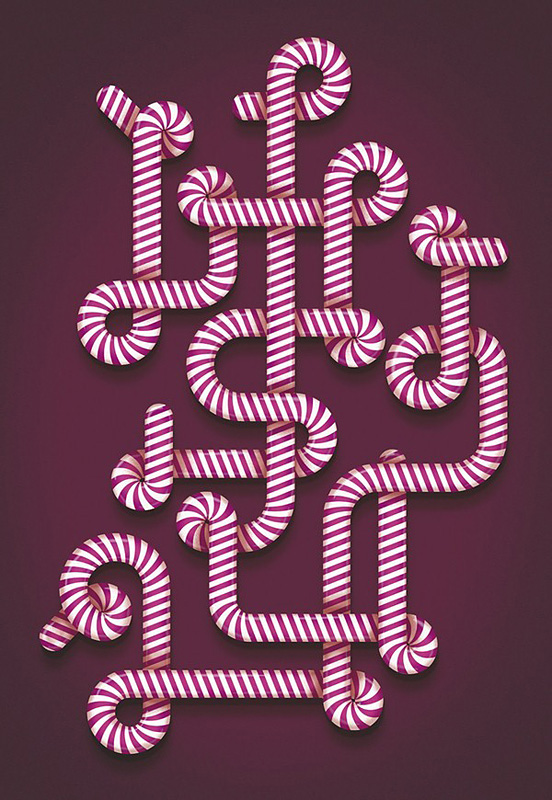
Акцидентный шрифт используют в заголовках, афишах, обложках книг, визитках и так далее. Его цель — привлечь внимание своей нестандартностью. Но чем необычнее выглядит текст, тем сложнее его читать, поэтому после акцидентного заголовка обычно идёт текст классическим наборным шрифтом.
Наборный шрифт используют в книгах, лонгридах, статьях и любых больших массивах текста. Его главная задача — сделать так, чтобы читать было легко и приятно, а глаза не уставали. Чем выше читабельность, тем лучше.
Примеры наборного и акцидентного шрифтаПропорциональный и моноширинный шрифты отличаются размерами литер.
Наглядный пример отличий пропорционального шрифта от моноширинногоВ моноширинном все буквы занимают одинаковую площадь, равную самой большой литере. Даже если английская буква i почти не занимает места, слева и справа от неё в моноширинном наборе будет много пустого пространства. Обычно его используют в таблицах, так как он помогает сохранить легкосчитываемую визуальную разрядность значений.
В пропорциональном занимаемая литерой площадь зависит от её размеров: английская i будет занимать в 2-3 раза меньше места, чем n. Такой набор экономит свободное место, поэтому в печатных изданиях используют только его. Если напечатать книгу моноширинным шрифтом, её объём и расход листов увеличится на 5-15%.
Типографика: искусство текста
4 — 2003Маргарита Григорян
Основа основ
Типографика на практике
Цвет
Если вы думаете, что книжки без картинок всегда очень скучные, то вы наверняка не знакомы с типографикой. Типографика это и наука, и искусство. Она превращает то, что принято называть голым текстом, в яркие и оригинальные графические образы.
По сути дела, типографика – это творческое преображение печатного текста в элемент графического оформления. Она обходится без использования иллюстраций и изобразительной графики, но с помощью моделирования и монтажа текста создает художественные образы. Именно поэтому типографика является неотъемлемой частью дизайна и оформительского искусства.
Главная задача типографики – доступно, ясно и в интересной форме донести до зрителя или читателя информацию. Как именно это сделать, остается на выбор специалистов по типографике – типографов. Они собирают в одно целое текст, шрифт, располагают шрифтовые элементы относительно друг друга и заданного пространства. Это может показаться простой и чисто технической задачей, однако на самом деле методами типографики можно создавать настоящие произведения искусства.
Типографика требует тонкого понимания процесса трансформации печатного текста в четкий визуальный образ, соответствующий значению заданной информации. Для этого существует множество различных приемов, например акцентирование смысловой нагрузки слова «оранжевый» при помощи написания его оранжевым цветом или же написание слова «маленький» небольшим кеглем. Также типограф может манипулировать гарнитурами шрифтов, разрядкой литер, их положением на макете, соотношением масштабов текстов и т.д. Поэтому типографов можно назвать художниками и поэтами одновременно.
Основа основ
Шрифт – это база для создания любой типографической композиции и, естественно, параметры шрифта ограничивают возможности типографа.
Чаще всего в типографике используются так называемые акцидентные и титульные шрифты, которые нецелесообразно применять для текстового набора. Они редко используются в мелком кегле, но хорошо смотрятся, как оформительские элементы при кегле покрупнее. Сегодня многообразие шрифтов постоянно пополняется новыми видами. Но, как ни странно, по мнению некоторых специалистов по типографике, обилие шрифтов является не показателем успеха, а наоборот, свидетельствует о недостаточной координации деятельности шрифтографов.
Типографика на практике
Огромное количество объявлений, вывесок и указателей выполнено в технике типографики. Широкое применение она находит и в малоформатных печатных изданиях; брошюры, флайеры, буклеты, проспекты и программки. Причина этого кроется в их предназначении привлечь внимание и донести информацию до читателя в условиях жестко ограниченного пространства бумажного листа. Типографика успешно справляется с обеими этими функциями, причем без перегрузки страниц тяжелыми иллюстративными элементами.
Не обходится без типографики и широкоформатная реклама. Поскольку взгляд задерживается на рекламном щите, как правило, не дольше чем на несколько секунд, информация на нем должна быть представлена в максимально сжатом виде. Такая реклама воспринимается сначала визуально, а лишь потом, если удастся привлечь внимание человека, происходит осмысление ее текстового содержания. При этом использование большого количества иллюстрирующих деталей может привести к негативному результату объявление оказывается перегруженным информацией и взгляд не успевает охватить одновременно и текст, и изображение и уж тем более правильно интерпретировать их. Здесь-то и приходит на помощь типографика, которая превращает текст в привлекающую внимание и легкую для восприятия графику. Проектируя широкоформатные рекламные плакаты, дизайнеры-типографы часто экспериментируют с соотношением масштабов текста и формата листа, находя порой довольно оригинальные композиционные решения. Именно в сфере рекламы у типографа появляется больше возможностей для трансляции заданного рекламодателем смыслового послания в композиционный образ.
Само собой, одной только широкоформатной рекламой применение типографики в рекламе не ограничивается типографическое оформление с успехом применяется и в печатной рекламе. Основные задачи здесь остаются теми же – привлечь внимание, заставить сначала всмотреться в образ, а затем и вчитаться в текст. Хороший пример – реклама «Finances, Trust, Consulting», разработанная дизайн-студией Open Design. Она представляет собой изображение прозрачной призмы, на гранях которой сделаны надписи «Деньги – это наука» и «Деньги – это искусство». Художники из Open Design использовали оригинальное и остроумное типографическое решение, заменив некоторые из букв кириллицы в надписи «Деньги – это наука» на греческие, которые, как мы знаем со школьной скамьи, широко применяются в науке, а в строке «Деньги – это искусство» – на музыкальные символы. Таким образом, смысловая нагрузка рекламы гармонично сочетается с ее визуальным исполнением. Нестандартное же решение делает рекламу заметной.
Широко используется типографика и в дизайне упаковки, причем наиболее часто она находит применение в парфюмерно-косметической индустрии. Практически все упаковки духов, как и этикетки на флаконах, выполнены с использованием типографики. Классическим примером может служить оформление легендарных духов «Chanel № 5», дизайн коробки которых не менялся с самого момента их создания в 20-х годах прошлого века.
Не устояли перед типографикой и просторы Всемирной сети. Существует довольно много Web-страниц, оформление которых построено исключительно на использовании оригинальной формы и начертания текста. Если такая страница с точки зрения дизайна создана грамотно, то она будет легко восприниматься зрителем и хорошо запоминаться. Поскольку в Web-дизайн типографика вносит элемент некоторой неформальности (все-таки в Интернете преобладает использование графических элементов для композиции и навигации), подобное оформление редко используется при создании корпоративных страниц, а вот среди сайтов дизайн-студий их становится все больше и больше. Один из наиболее известных и интересных сайтов такого рода – The Designers Republic (http://www.thedesignersrepublic.com/). Он представляет собой обширный каталог дизайнерских решений, и именно благодаря типографическому оформлению навигация среди огромного количества информации заметно упрощается. На главной странице The Designers Republic можно увидеть большую типограмму с надписью «Angryman» – текст, посредством монтажа превращенный в изображение «сердитого человека». Всмотревшись в эту типограмму, зритель увидит детали латинских литер, собранных в одно целое.
Часто в типограммах (или в «каллиграммах») на первый взгляд невозможно определить первоначальный облик отдельных символов, но, если присмотреться, можно различить их. При создании типограмм типографы обычно пользуются такими приемами, как искажение составных литер, изменение кегля и рисунка символов, а также намеренная деформация строк наборного текста. Самый простой и распространенный способ создания типограмм – верстка текста в форме описываемого в нем объекта (например, указатель, в котором размеры составляющих его букв подобраны таким образом, чтобы слово по форме напоминало стрелку). Но есть и более сложные разновидности типограмм, в которых текст становится нечитаемым, преобразуясь в картинку. «Angryman» с The Designers Republic – отличный тому пример.
Без типографики не существовало бы логотипов. Даже самые простые из них представляют собой типографические композиции, а многие и вовсе являются сложными типограммами. Бывает даже так, что шрифт, использованный в логотипе, сам по себе начинает восприниматься как неотъемлемая часть корпоративного имиджа компании, например, как известный шрифт Microsoft Sans Serif.
Типографика пользуется огромной популярностью и у авторов художественных постеров и плакатов, которые давно уже выделились в самостоятельный жанр изобразительного искусства. Они, как и рекламные публикации, вынуждены апеллировать в первую очередь к визуальному восприятию. Однако жанр постеров и плакатов не органичен такими жесткими рамками, как, скажем, печатная реклама, и поэтому дает дизайнерам большую возможность художественного самовыражения; отсутствие заданных рекламодателем слоганов и формулировок превращают текст в полноправный инструмент графического оформления. Крупный формат плаката только усиливает его выразительность. Любопытный пример – антирасистский постер, созданный дизайн-студией Open Design. На нем изображены символы четырех мировых религий, каждый из которых собран из печатного текста, взятого из священной книги другой веры. Например, мусульманский полумесяц набран текстом из Торы, а шестиконечная звезда Давида – строками из Корана. Однако значение подобных постеров может остаться непонятным без сопроводительной пояснительной надписи. В данном случае это строки «Они – это мы» и «Мы – это они», расположенные на красной ленте, согнутой буквой V символично, просто и понятно.
Типографика в веб-дизайне — правила и тренды современной типографики
“Веб-дизайн — это 95% типографики”, — сказал основатель компании Information Architect Оливер Райхенштейн. Так оно и есть: без качественной типографики ваш сайт будет неудобным для восприятия. В этой статье разберем основные виды типографики и современные тренды. Поехали!
Что такое типографика и зачем она нужна
Типографика в веб-дизайне — это свод правил оформления текста и графических элементов сайта, который несет определенный посыл, воздействует на эмоции и мотивирует посетителя к совершению целевых действий. В зависимости от направления сайта эти действия могут быть разными: подписаться на рассылку, читать больше статей, оставлять комментарии, совершать покупки. Таким образом, типографика идет рука об руку с продающим дизайном.
Есть еще дельное определение. Типографика — наука об эргономике текста, созданная для того, чтобы текст как можно легче читался и воспринимался посетителем сайта. Для этого должен соблюдаться баланс текстовых и графических элементов
Основные правила типографики
- Чем проще — тем лучше. Даже если появилось множество новых интересных шрифтов, эмодзи, анимаций — не нужно использовать все их сразу. Сайт будет аляпистым и совершенно не стильным.
- Сайт должен быть читабельным. Если выбирать между оригинальностью идеи и удобством для посетителя — любой веб-дизайнер не раздумывая выберет второе.
- Главное должно отличаться от второстепенного. Хорошая типографика сразу показывает, что тут самое важное, а что нет. Если элементы сайта спорят между собой и взгляд посетителя мечется, не зная, что выбрать — значит, типографика хромает.
- Правило золотого сечения. Мы уже писали о нем в статье про основные правила веб-дизайна. Если кратко — это деление элементов страницы сайта на пропорции в соотношении 3/2, или 5/3, и так далее. Чаще всего по этому принципу определяется соотношение рекламных блоков и текста.
- Текст важнее. Графика должна не перетягивать одеяло на себя и отвлекать от контента, а дополнять его и привлекать к нему внимание. Текстовая информация чаще важнее, чем картинки — а значит, графика должна быть на службе у контента, а не наоборот.
- Помните о гармонии. Не только в музыке она есть, как пелось в одной известной песне. На сайте все должно быть выполнено приятно глазу, гармонично и естественно. Хотите проверить? Просто дайте оценить сайт любому знакомому: пусть посмотрит свежим взглядом и выскажет честное мнение.
Основные понятия типографики и как их применять
О шрифт, ты — мир!
История шрифтов в типографике заставляет задуматься. На заре веб-дизайна считалось крутым использовать необычные шрифты по принципу “чем чуднее — тем моднее”. Со временем появилась тенденция к упрощению: сейчас предпочтение отдается простым крупным шрифтам. И обязательно читаемым.
Приведем несколько основных правил использования шрифтов на сайте:
1. Не используйте слишком много шрифтов. Мы все понимаем — хочется сделать свой сайт поярче и поинтереснее, но пожалуйста, остановитесь на двух-трех. Слишком большое количество шрифтов выглядит непрофессионально и нечитабельно. Подумайте о посетителе — легко ему будет подстраиваться под хотелки дизайнера? Да и сочетать много шрифтов будет непросто — как правило, в итоге таких экспериментов получается сборная солянка.
Например, хорошо сочетаются шрифты Georgia и Verdana — они визуально похожи и гармонично дополняют друг друга. Шрифты Baskerville и Impact, напротив, имеют разную ширину символов, и второй просто “убивает” первый.
2. Используйте стандартные шрифты. Если ваш веб-дизайнер — не суперпрофессионал, лучше не рисковать и выбрать знакомые всем true-шрифты, которые давно зарекомендовали себя. Это, например, системные Arial или Calibri, можно также использовать шрифты Google (это бесплатно) или Adobe Typekit (по подписке) или поюзать онлайн-конструкторы. Вариантов масса!
Внимание! Этот способ могут не применять те, кто хочет сразу громко заявить о себе или создать фирменный стиль сайта. Вот тут можно экспериментировать вволю — конечно, заручившись помощью хорошего дизайнера. С осторожностью обращайтесь с готическим, старославянским шрифтами, Comic Sans — они, как нам кажется, давно себя изжили и не всегда уместны. Хотя на многих ресурсах до сих пор популярны.
3. Буквы должны читаться! Есть некоторые шрифты, в которых отдельные буквы можно перепутать. Например, I и L в английской раскладке, “н” и “м”, “т” и “ш” — в русской. Особенно сложно бывает читателю, когда еще и расстояния между буквами маленькие. Остерегайтесь таких шрифтов!
4. Выбирайте адаптивный шрифт. Про адаптивный дизайн сайта, который одинаково хорошо просматривается и грузится на разных устройствах, уже всем известно. Пользователи заходят в сеть со смартфонов, планшетов, ноутбуков, лэптопов — размеры экрана у них у всех разные, разрешение тоже отличается. Шрифт — часть адаптивного дизайна, он должен так же хорошо читаться с различных устройств и в разных размерах. Избегайте слишком маленьких шрифтов, чтобы пользователю не приходилось приближать текст и совершать дополнительные действия.
Искусство цвета
1. Играйте на контрасте. Цвет текста и фона для него должны различаться. Серый на сереньком — так себе тренд. Чем больше бросается в глаза контраст — тем гарантированнее он привлечет внимание пользователей. Чем меньше шрифт, тем более он должен быть контрастным, и наоборот.
Какие цвета можно сочетать? Используйте базовые принципы сочетания цветов. В этой схеме нет черного и белого — они априори сочетаются с любым цветом. Наиболее контрастным, кстати, считается сочетание черного и желтого. Взять наш “Тинькоф-журнал” — они использовали это правило на все сто.
2. Смелее, детка! В моде техники градиента, дуплекс — использование двух цветов и их полутонов, трехмерные объемные изображения, картинки, нарисованные вручную и другие тренды веб-дизайна 2018 — ограничений практически нет. Все зависит от вкуса и чувства стиля вашего дизайнера.
3. Выделяйте цветом важнейшие текстовые блоки и рекламу — чтобы посетитель сразу обратил на них внимание. Многие дизайнеры советуют избегать красного и зеленого цветов — заботятся о больных дальтонизмом. Между прочим, среди мужчин дальтоников аж восемь процентов — серьезное число.
Оформление текста
“Крылья, ноги, главное — хвост!” — если перефразировать фразу из культового мультика, то же самое можно сказать и о тексте. Цвет и шрифты, конечно, важны, но оформление текста все же играет главную роль в восприятии сайта посетителем. Рассмотрим современные тенденции оформления текста:
1. Используйте пиктограммы, значки, эмодзи. В типографике как в жизни: если люди активно используют смайлики для общения, значит, нужно применять их и на сайтах. Мир веб-типографики уже никогда не станет прежним: пиктограммы, смайлы и значки стали важной частью текста. Это делает его более динамичным и близким к пользователю.
2. Форматируйте. Это незыблемое правило: если не хотите, чтобы ваш интересный и полезный текст превратился в одну большую простыню — ставьте заголовки и подзаголовки, не забывайте про маркированные списки. Обязательно выделяйте абзацы — сплошной текст читать просто невозможно. Считается, что оптимальная длина абзаца составляет 3-5 строк.
Для того чтобы расставить акценты, выразить главные мысли — прибегайте к выделению жирным, подчеркиванию и курсивом. Эффект зачеркивания круто смотрится, когда надо добавить иронии. Из журнальной типографики к нам пришли вынос мыслей в цитаты, красивое оформление первых букв нового абзаца.
3. Забудьте про капслок! Тренд выделять главное капсом давно умер: сейчас большие буквы воспринимаются как крик и вызывают у читателя лишь негатив. Большие буквы уместны лишь в заголовках, да и то не всегда. Привлекать внимание с помощью капса уж точно не рекомендуется.
4. Ограничьте длину строки. Помните базовое правило типографики: текст важнее графики, особенности дизайна не могут диктовать условия верстке текста. Если дизайн вашего сайта предполагает длиннющую строку — проще поправить дизайн, чем заставить читателя дочитать ее до конца. Читабельность превыше всего!
Эксперты говорят, что оптимальное количество символов на строку — не более 60. Если меньше — читатель будет слишком быстро возвращаться в начало строки и сбивать ритм чтения. Если больше — сложно будет сосредоточиться на тексте: пока подойдешь к концу строки, забудешь о том, что написано в ее начале.
Внимание! Это правило актуально для текстов, которые читаются с ПК. Если речь идет о мобильном устройстве, длина строки должна составлять не более 30-40 символов — больше в экран просто не влезет. Ну вы поняли: адаптивный дизайн — наше все.
5. Следите за межстрочным интервалом. Чем он больше — тем больше воздуха в тексте, тем проще читателю пробираться через слова и символы. Обычно размер интервала должен быть на 30% больше высоты символов. Посмотрите, какая колоссальная разница между первым и вторым примером!
Тренды типографики последних лет
Типографика переживает сейчас настоящий расцвет: мы наблюдаем буйство стилей и эффектов, разнообразие визуальных составляющих, новые способы воздействия на посетителей.
Крупная типографика
Пожалуй, самый главный тренд последних лет — крупная типографика. Давайте разберем, зачем она нужна:
- привлекает и удерживает внимание посетителя. Сложно не заметить крупные шрифты, яркие цвета и особое расположение самого важного текста на странице. На сайте интернет-магазина, например, таким текстом будет призыв к действию, информация о скидках и поступлении новых коллекций. На новостном сайте — самая актуальная в данный момент статья. Большой текст — как неоновая надпись в небе: ну посмотри же на меня, прочитай меня, выбери меня, купи меня;
- вызывает эмоции. Если написать одну и ту же фразу мелким и крупным шрифтом — посетитель стопроцентно отдаст предпочтение второму варианту. Вопрос еще и в том, как написать — если удастся воздействовать на чувства посетителя — велик шанс, что он вернется и станет вашим постоянным посетителем. Если за громким слоганом стоит личность создателя сайта — эффект может быть ошеломительным. Главное — не только сказать, но и кем это сказано;
- позволяет определить главное. Все слышали про эффект баннерной слепоты — когда посетитель бегло сканирует взглядом текст, не задерживаясь на отдельных элементах. Крупный заголовок или рекламный баннер позволяет отделить зерна от плевел и остановить взгляд на самом главном. Заголовок помельче — информация второго уровня важности. Ну и так далее.
Большие шрифты
Жирный, еще жирнее! Это не оскорбление, а тенденция шрифтов последних лет. Чем больше и жирнее шрифт, да еще и с насечками — тем более современной будет ваша типографика. Кроме того, такие шрифты отлично читаются с мобильных устройств — мы же знаем, что все больше людей заходят на сайты со смартфонов и планшетов.
Сломанные сетки
Макеты с классической сеткой уже не в моде — дизайнеры отказываются от них и буквально пускаются во все тяжкие! Типографика сайта все больше напоминает издательский дизайн. Разметка на блоки, строгое количество колонок текста, модули уже не придерживаются строгих правил и живут своей жизнью. Каркас сайта может быть совершенно разным — главное, чтобы посетителям нравилось.
Больше движения!
Активно используйте гифки, анимацию, 3D-типографику — это оживляет сайт, привлекает внимание посетителей и выделяет ваш дизайн на фоне других. Особенно хорошо эти приемы работают при создании фирменного стиля сайта и персонализации личного бренда. За рубежом анимация давно популярна — у нас еще не все оценили ее возможности. Не упускайте шанс!
Понравилась статья? Обращайтесь в IDBI — мы знаем о типографике все и поможем разработать ваш сайт с учетом новых тенденций.
Леонид Рабинович «Что такое типографика?»
Данная статья написана Леонидом Рабиновичем и опубликована в его персональном блоге. Статья дает вводную информацию для начинающих изучать типографику, верстку и шрифт.
Текст — это последовательность слов. Текст остается текстом, вне зависимости от того, где он находится. Я могу написать «Люблю эспрессо и омлет» и распечатать это на бумаге, могу отослать сообщением ВКонтакте, могу просто сохранить текстовый файл и держать у себя на компе. Текст будет одинаковый, а носители разные.
Но когда мы печатаем (пишем, набираем и т.д.) «Люблю эспрессо и омлет» — в силу вступает типографика. Любой отображаемый текст — типографика. Без разницы на каком формате он написан.
Типографика влияет на содержание или смысл, то есть может решать разные задачи. Например, когда мы читаем книгу, нам важно чтобы наши глаза не перескакивали со строчки на строчку, чтобы шрифт был читаемый, чтобы мы легко ориентировались в содержании. Или когда на дороге нам встречаются разные знаки. В этом случае типографика должна быть ясна, а шрифт считываться за доли секунд. Представьте что будет, если весь текст на указателях писать каллиграфией.
Подумайте в чем разница между двумя следующими страницами: в тексте или типографике?
Текст ок
Текст не ок
Разница только в типографике. Этот пример ясно показывает как типографика влияет на комфорт и удобство, в данном случае, чтения.
Можно ли отнести типографику к искусству, я не знаю. Но думаю, что можно. По сути типографика должна быть функциональна, например функция передачи информации, и эстетична — подать информацию красиво.
Я считаю, что типографика — это основа всего графического дизайна. С помощью слов мы можем больше и точно передавать информацию, нежели чем с помощью картинок.
(!) Шрифты являются частью типографики, но типографика выходит за рамки шрифта.
Выводы:
- Типографика — это любой отображаемый текст.
- С помощью типографики можно решить разные задачи, влиять на удобство восприятия и на содержание предмета.
Шрифты — лишь часть типографики.
Почитать по этой теме:
http://artgorbunov.ru/bb/soviet/20140101 — совет Антона Шнайдера о значении типографики.
http://pajasu.livejournal.com/1241317.html — Принципы хорошей экранной типографики (кратко)
http://www.artlebedev.ru/kovodstvo/business-lynch/kagarov — Бизнес-линчи Эркена Кагарова (он всегда объясняет почему «типографика хуевая», например)
Следующий пост будет по теме:
Для кого нужна типографика?
Автор: Леонид Рабинович
Типографика в дизайне | Статья в журнале «Молодой ученый»
В статье описывается понятие типографики. Раскрывается определение шрифта и его составляющих. Подробно рассматриваются правила работы с типографикой в веб-дизайне. Автор уделяет внимание важности соответствия шрифта проекту.
Ключевые слова: типографика, шрифт, адаптивный дизайн, засечка, веб-дизайн.
Типографика одна из важных составляющих дизайна и ключевой инструмент при проектировании сайтов. Люди взаимодействуют с ней на протяжении многих веков. В данной статье большое внимание уделяется рассмотрению типографики в контексте веб-дизайна.
Современная типографика — это искусство, которое призвано сделать сложный материал простым, а неинтересный товар — популярным [3].
Неотъемлемая и главная часть типографики — шрифт.
Шрифтом обычно называют графическую систему изображения знаков, имеющую свойственное только ей начертание [2]. Единицей шрифта считается буква.
Русскоязычные специалисты и обычные пользователи в большинстве случаев используют кириллические и латинские шрифты. Кириллический шрифт моложе латинского. Это связано, в первую очередь, с пересмотром состава кириллицы Петром I. Была проведена реформа, и для светской и уставной печати начали использовать антикву. Последующие века шрифт трансформировался и видоизменялся. Это длительный процесс, который происходит и сейчас.
Шрифт отражает идею проекта, так как способен повлиять на отношение к проекту. Существует несколько категорий шрифтов. Во-первых, шрифты делятся на две большие группы: с засечками и без засечек. Это необходимо знать как типографам и дизайнерам, так и верстальщикам.
Засечка, или сериф, — один из важнейших элементов шрифта. Настолько важный, что, даже если в самом шрифте нет засечек, упоминание о них все равно есть в названии класса таких шрифтов: sanserif — «без засечек» [1].
Существют следующие виды шрифтов:
— — Антиква — шрифты с засечками.
Антиква подразделяется на следующие категории: старого стиля, переходная, нового стиля, латинского стиля, брусковая. Первая наборная антиква поялилась в Италии и Германии в начале XV века.
— Гротески (рубленные) — шрифты без засечек.
Классификация гротесков: старые гротески, новые гротески, геометрические, гуманистические, антиква и прочие.
— Готические — данные шрифты были распространены в XIII-XVI веках. Различают следующие виды готических шрифтов: текстура, швабахер, фрактура, ротунда.
— Акцидентные — предназначенные для акцидентного набора. К ним иногда относят и рукописные шрифты.
Следует подробнее остановиться на акцидентных шрифтах. Акцидентный шрифт отличается от наборного своей декоративностью, выразительностью и архитектурой. Он может быть менее читабелен, но главная информация должна считываться посредством визуальных образов. Основная цель акцидентного шрифта — привлечь внимание потребителя, пользователя или читателя.
Из этого следует, что у каждой из этих шрифтовых групп свои задачи. Гротески XX века хорошо справляются с нейтральными задачами. Шрифт передает потребителю не только прямое содержание сообщения, но и вызывает у человека определенные ассоциации. Этот эмоциональный отклик зачастую субъективен, ведь он основывается на жизненном опыте человека и степени его образованности, однако посредством опроса фокус-групп были выявлены схожие реакции на определенные виды гарнитур [2].
То есть, необходимо смотреть на все шрифты через контекст истории и принадлежности к стилю. Это необходимо для передачи характера бренда. Дизайнеру следует для начала выявить задачу и только потом подбирать шрифт. Многие люди не замечают соответствия шрифтов для айдентики или сайтов, в которых выбранная гарнитура используется. Но если потребитель не осознает этой взаимосвязи, совершенно не значит, что ее нет. Мы можем испытывать когнитивный диссонанс или недоверие к бренду на интуитивном и подсознательных уровнях.
Есть определенные правила работы с типографикой. И если в графическом дизайне и плакатном искусстве дизайнеры часто нарушают правила для достижения определенных декоративных эффектов, то не стоит ими пренебрегать в верстке книг и журналов, а также в веб-дизайне и разработке мобильных приложений.
В контексте веба правильная работа с типографикой играет важную роль. Одной из главных причин этого является важность структурирования контента в веб-пространстве. Это продиктовано феноменом клипового мышления.
Чем больше элементов использовано, например, на сайте, в буклете или листовке, тем разнообразнее они по своему содержанию и оформлению, тем выше потребность в четкой структурированности пространства. В данном случае основной задачей типографики является становление частью графических композиций [5]. Правила типографики обширны, ибо они включают в себя: все параметры шрифта (начертания, кернинг, кегль, интерлиньяж и т. д.), расположение текста, тонкости расстояний между параграфами, красной строки в русской типографике, её уместное использование, а также расстояние между заголовками и основой массой текста и т. д. [4].
Рассмотрим основные правила работы с типографикой в вебе.
— Размер пункта — это размер шрифта. В печати наиболее удобный диапазон для основного текста — 10–12 пунктов. В Интернете — 15–25 пикселей.
— Межстрочный интервал — это расстояние между строками по вертикали. Он должен составлять 120–145 % от кегля. При верстке сайта, пользуясь каскадными таблицами стилей (CSS), можно использовать свойство line-height.
— Длина строки — это ширина текстового блока по горизонтали. Длина строки должна составлять в среднем 45–90 символов в строке
— Для грамотного структурирования контента важно использование различных начертаний. (Regular, Bold, Light).
— Висячих предлогов следует избегать.
— Если расстояние между символами выглядит неровно, можно поправить его с помощью кернинга, руководствуясь правилом: «Пространство между символами должно быть одинаковым».
При соблюдении этих правил проект будет выглядеть композиционно правильным, текст будет хорошо считываться и восприниматься пользователем.
В заключение необходимо подчеркнуть, что типографика в дизайне является первостепенным элементом, наряду с композицией. Она важнее анимации и ярких графических решений. Кроме того, она выполняет функции инклюзивного дизайна, рассчитанного на доступность всем. Поэтому необходимо выбрать правильный и соответствующий идеям проекта шрифт, подобрать оптимальные размеры, кегль и интерлиньяж. В веб-дизайне функциональность всегда важнее графических решений. Дизайнеры делают продукт для человека, и он должен быть удобным, простым и понятным.
Литература:
- Гордон Юрий. Книга про буквы от Аа до Яя. — Москва: Издательство студии Артемия Лебедева, 2006. — 384 с.
- Каменская А. А. М. Е. Карагодина Основные принципы работы со шрифтами в графическом дизайне // Дизайн и архитектура: синтез теории и практики: сб. науч.тр. — Краснодар: Кубанский гос. ун-т, 2018. Вып. 2. — С.131–134.
- Любодарская К. В. Графический дизайн в системе маркетинговых коммуникаций на b-2-b рынке // Маркетинговые коммуникации. 2013. № 2. С.86–95.
- Мамаева Д. М. Взаимосвязь типографики и фирменного стиля. [Электронный ресурс]. — URL: https://www.elibrary.ru/item.asp?id=43131906
- Старикова Е. А. Типографика как новая современная форма коммуникации в дизайне // Лучшая научная статья 2016: сбрник статей II Международного научно-практического конкурса. — Пенза: МЦНС «Наука и просвещение». — 2016. — С.67–72.
Основные термины (генерируются автоматически): шрифт, засечка, CSS, XIII-XVI, акцидентный шрифт, век, длина строки, идея проекта, правило работы.
Типографика, история и задачи. Типографика, история и задачи С кем работают графические дизайнеры
Типографика – процесс и искусство разработки архитектуры коммуникации; моделирование, графическое оформление материала посредством набора и верстки, на основе определенных правил, специфических для данного языка.
Типографика — это искусство предоставления текстовой информации, преображение текста в графическое оформление, основа графического дизайна.
Термин типографика происходит от греческого τύπος — отпечаток + γράφω — пишу) — искусство оформления печатного текста.
Типографика – это, с одной стороны, набор правил, определяющих использование шрифтов и оформительских средств, с другой стороны – искусство графического дизайна.
Цель типографии – упростить коммуникацию с аудиторией, улучшить восприятие передаваемой информации.
Задачи типографики , наиболее творческого этапа оформления текста, предполагают:
- определение параметров для последующих процессов набора, вёрстки и допечатанной подготовки;
- способствование передаче эмоции, настроения, отношения задуманных автором, вовлечение в чтение и изучение;
- моделирование вида и формы контакта аудитории с объектом авторского и дизайнерского творчества;
- сделать текст наиболее оптимальным, ясным, максимально обеспечивая удобочитаемость текста;
- сделать текст интересным в восприятии читателя, зрелищным, гармоничным в общей структуре коммуникации.
Типографика в маркетинге – инструмент и средство, обеспечивающее лучшую коммуникацию с целевой аудиторией. Типографика определяет общий формат итогового маркетингового материала:
- пропорции, формат полосы набора, раскладку полей;
- параметры шрифта: кегль, интервалы между словами и строками;
- размеры, место расположения и меру зрительной «тяжести» иллюстраций.
Типограф – специалист, занятый топографический деятельностью: художественный и технический редактор, оформитель и художник, каллиграф и проектировщик шрифтов, графический дизайнер – все те, кто так или иначе сталкивается с типографикой. Типограф в маркетинге – посредник между владельцем, производителем товара, разработчиком его рекламных коммуникаций и целевой аудиторией.
История типографики начинается с середины XV века, когда формируются первые основы типографики: используется удобочитаемая «Антиква»; вводится принцип равномерности интерлиньяжа и азбучного отступа. В XVI века в типографику вводится понятие «курсив». В XVII веке типографика меняет свои задачи с целью создания книг для широкого круга читателей – уменьшается формат книг, видоизменяются шрифты, особую роль принадлежит Дж. Баскервиллу, отказавшемуся от использования орнамента в пользу именно типографики, исключительно основанной на шрифтовом оформлении.
Многие вообще никогда не слышали о таком термине как «типографика». И даже те, кто его слышал, имеют весьма далеко представление о том, что же это собственно такое. На самом деле типографика – это преображение того, что принято называть текстом в яркие элементы графического оформления. Именно текст на страницах книг, журналов или web-сайтов несет в себе основную информацию. И очень важно, чтобы он был грамотно оформлен, чтобы привлечь внимание читателя и в доступной, интересной форме донести до него основную суть. Этим и занимается типографика, которая является неотъемлемой частью графического дизайна и оформительского искусства.
Понятие типографики, история и задачи
Существует множество определений такому понятию, как типографика. В наиболее общем виде можно сказать, что типографика представляет собой графическое оформление печатного текста с помощью набора и верстки на основе определенных правил, специфических для данного языка. Типографика – это, с одной стороны, искусство графического дизайна, а, с другой стороны, набор правил, определяющих использование шрифтов и оформительских средств для того, чтобы сделать текст наиболее оптимальным, ясным и интересным в восприятии читателя. С помощью моделирования и монтажа текста специалисты этой области создают оригинальные художественные образы, делают текст живым, придают ему способность передавать идею не только своим содержанием, но и графической составляющей.
В принципе, к типографической деятельности можно отнести работу печатников и наборщиков, авторов и редакторов изданий, художественных и технических редакторов, оформителей и художников книг, каллиграфов и проектировщиков шрифтов, графических дизайнеров и полиграфистов. Их работа, так или иначе, связана с типографикой. Типограф выступает посредником между автором текста и читателем, видоизменяя печатные формы таким образом, чтобы передать содержание наиболее полно и интересно.
С типографикой также тесно связана такая деятельность, как проектирование рекламы, вывесок, оформление выставок, разработка многочисленных элементов фирменного стиля, создание дизайна web-сайтов. Особенно типографика востребована в рекламе, ведь текст в рекламе является важнейшей составляющей, позволяющей рекламодателям заявить о себе.
Нельзя сказать, что типографика как явление появилось только на рубеже XX – XXI веков. В действительности, история становления и развития типографики начинается с появления в жизни человека книгопечатания. Более того, своими корнями эта область графического дизайна уходит еще в более древнюю эпоху рукописных книг, когда красивое размещение текста на плоскости листа очень ценилось. Уже с середины XV века формируются первые основы типографики: в Европе в качестве шрифта для текстов используется удобочитаемая антиква, также издатели и авторы книг начинают выдерживать принцип равномерности интерлиньяжа и абзацного отступа как средства выделения и структурирования текста.
А в начале XVI века в обиход типографики впервые вводится курсив. В этот период книги начинают отличаться все более изощренным и оригинальным шрифтовым оформлением, одновременно утрачивается сходство шрифта с рукописным. Европейские книжные издания XVI столетия характеризуются тонально-живописным характером иллюстраций и богатым декором, включающим в себя и орнаментальные бордюры.
В XVII веке с подачи издательских домов Голландии типографика меняет свои задачи в пользу создания книг для более широкого круга читателей. Соответственно, книги приобретают небольшой формат для большего удобства, видоизменяются шрифты – они получаются с более утяжеленным рисунком, что позволяет сохранять четкость оттиска даже при больших тиражах изданий. В это же столетие появляется оригинальный шрифт «Королевская антиква», еще дальше отходящий от рукописного прототипа. В середине XVIII века впервые появились попытки систематизации типоразмеров и выпуска книг шрифтовых образцов.
Особую роль здесь сыграл англичанин Дж. Баскервилл, который отказался от использования книжного орнамента в пользу «чистой» типографики, основанной на исключительно шрифтовом оформлении. Типографика стремительно меняется – появляется геометрическая строгость шрифтового рисунка, выявляется композиционная значимость свободного пространства книжного листа, разрабатываются новые отточенные, контрастные шрифты для книгопечатания.
Промышленная революция способствовала разработке новых видов и разновидностей шрифтового рисунка для целей рекламы и периодики. В XIX столетии в обиход книгопечатания вводятся шрифты жирных начертаний, египетские шрифты, гротески, также возрастает значение книжных орнаментов и иллюстраций. В то же время критика обезличенного машинного производства привела к возрождению некоторых ручных типографских процессов.
На рубеже XIX — XX столетий в типографике, как и в других видах оформительского искусства, становится популярным стиль модерн с характерной для него экспрессией органических форм и декоративно-силуэтных иллюстраций, что, естественно, обеспечило поиск новых шрифтовых рисунков. Для этого же периода времени характерно возникновение экспрессивной типографики, целью которой являлось воссоздание образности авторского повествования посредством перемены шрифтовых кеглей и начертаний.
В первой половине прошлого века типографика развивалась уже в неоклассическом ключе, то есть на первый план вышла удобочитаемость каждого знака текста в целом, а также простота шрифтового рисунка. В 40 – 60-е годы типографика приобрела более деловой характер, что привело к упорядочению книжной композиции, приведению к единому оформлению всех визуальных элементов книги.
В качестве композиционного каркаса книги стала использоваться математически рассчитанная модульная сетка, состоящая из равных прямоугольников текста и свободных промежутков между ними. Такая композиция выдерживалась в изданиях от первой до последней страницы. В 1970 году в Нью-Йорке была основана Международная шрифтовая корпорация (ITC), которой принадлежит огромная роль в разработке новых шрифтов, в том числе хорошо известных нам сегодня. Как мы видим, каждая историческая эпоха характеризовалась своей типографикой и созданием своих собственных шрифтовых рисунков, отвечающих конкретным задачам и веяниям времени.
На современном этапе задача типографики заключается в том, чтобы доступно, в ясной и интересной форме донести до зрителя или читателя определенную информацию. Для этого специалисты по типографике (типографы) собирают в одно целое текст, выбирают шрифт, размещают определенным образом шрифтовые элементы относительно друг друга и заданного пространства. Несмотря на то, что такая работа кажется чисто технической задачей, методами типографики можно создавать настоящие произведения искусства.
Если типограф работает с книгой, то он полностью разрабатывает ее архитектуру, то есть формат строки и полосы набора, раскладку полей, кегль и размеры шрифта, интервалы между словами и строками, место расположения иллюстраций в тексте. В результате получается хорошо продуманная, подчиненная определенному замыслу книжная страница и печатное издание в целом, которые выполняют как сугубо функциональное назначение (удобочитаемость текста), так и характеризуются зрелищной, художественной структурой. Если же речь идет о web-дизайне, то здесь профессиональный типограф занимается выбором правильного написания текста для повышения читабельности информации на сайте и привлечения посетителей. Неправильный выбор типографики может привести к тому, что сайт получится достаточно скучным и у посетителей не возникнет никакого желания оставаться на нем.
Типографическое оформление текста
Типографическое оформление текста зависит от нескольких составляющих:
— Назначение текста. Очевидно, что текст для наружной рекламы – совершенно не одно и тоже, что журнальный текст или даже рекламная информация, размещаемая на сайте. В зависимости от того, что представляет собой текст и каково его назначение должны использоваться те или иные выразительные средства.
— Носители текста. Также на выбор типографических приемов влияет то, где будет размещаться текст – в Интернете, на рекламном щите или бумаге глянцевого издания.
Выбирая те или иные способы оформления текста в зависимости от его назначения и содержания, типограф работает над достижением нескольких целей. Во-первых, это удобочитаемость текста – свойство, характеризующее удобство восприятия информации человеком. Особенно удобочитаемость важна в текстах, предназначенных для сплошного чтения. Удобочитаемость обеспечивается не только графическим исполнением шрифтов или правильным структурированием текста, но и мерами стилистики или семантики.
Во-вторых, необходимо обеспечить заметность текста, особенно это касается рекламной информации. Здесь типограф оперирует цветом символов или фона, выделительным шрифтом и другими средствами. В-третьих, задача специалиста по типографике состоит в том, чтобы сделать текст различимым. Данное требование важно для чтения в условиях пониженной видимости или за короткое время. Различимость обеспечивается, например, крупным кеглем или сильным контрастом цветов текста и фонового рисунка.
Естественно, что главное, с чем работает типограф – это шрифт, поскольку от него в основном зависит восприятие текста читателем. Шрифт представляет собой набор символов определенного размера и рисунка. Различные шрифты объединяются в группы или семьи по своему стилистическому решению: шрифты рукописные, шрифты с засечками или без засечек и другие. Понятием «гарнитура» в типографике как раз и определяют шрифт или несколько шрифтов, обладающих стилистическим единством начертания. Например, гарнитура TimesNewRoman включает в себя обычный, курсивный, полужирный и множество других шрифтов этого, очень популярного сегодня семейства.
Различные виды шрифтов могут по-разному влиять на восприятие и настроение читателя. В печатных материалах широко применяются шрифты с засечками, так как засечки помогают создать пространство между буквами, а иногда дают ощущение чего-то личного или выражают некое уважение. Шрифты без засечек, в свою очередь, используются при оформлении текстов, размещаемых на web-страницах. Ведь при низком разрешении компьютерного монитора засечки будут выглядеть размытыми, а сам шрифт с засечками будет несколько размываться. Также шрифты без засечек способствуют выражению чувства стиля, молодости и современных тенденций.
При оформлении текстов для бизнес-проектов предпочтительны традиционные гладкие шрифты, благодаря которым текст будет восприниматься более серьезно. Выбирая тот или иной шрифт, типограф исходит не только из назначения текста, но и из его содержания и смысла. В этой связи, например, счастливые сообщения рекомендуется сопровождать легкими и мягкими формами шрифтов, а мрачные, наоборот, шрифтами с более жесткими очертаниями.
Помимо шрифтов, типограф работает с такими типографическими понятиями, как интерлиньяж (расстояние между базовыми линиями соседних строк) и кернинг (подбор интервала между буквами для повышения удобочитаемости текста). Важным является также контрастность и цвет текста. Как правило, выбирается тот цвет, с помощью которого текст будет выделяться из фона и при этом оставаться удобным для чтения. Цвет текста должен заставить людей остановить свой взгляд и вчитаться в него.
При этом в типографике не забывают о контрастности и цветовых комбинациях текст – фон. Правила типографики говорят нам о том, что употреблять такие сочетания, как серый текст на светло-сером фоне или желтый текст на красном фоне не стоит. Шрифт близкого к фону оттенка практически всегда плохо различим, а излишняя контрастность, в свою очередь, нередко раздражает читателя.
Еще одна важная составляющая типографики – это система ориентирования, то есть система пиктографических и текстовых элементов, которая призвана помочь читателю находить в тексте необходимую ему информацию. Система деления текста должна включать в себя подчиненные заголовки различного уровня, выражающие взаимосвязь и соподчиненность возглавляемых ими текстовых частей. Сами заголовки и подзаголовки в тексте могут отличаться различной цветовой гаммой, подчеркиванием или графическим текстом в зависимости от содержания и назначения информации.
Типограф работает над определением того, в каких местах нужно размещать текст, и каковыдолжны быть его размеры. Первым шагом к этому будет выяснение, какая информация является наиболее важной в предлагаемом тексте. Ее обычно и выделяют размерами шрифта или свободным пространством. Вообще, типографика утверждает, что свободное пространство имеет большое значение в тексте, поскольку позволяет ему «дышать». Например, слишком широкие строки с текстом утомительны для глаз человека и способствуют возникновению неблагоприятного психологического эффекта.
А вот наличие свободного пространства вокруг текста снижает напряжение и позволяет читателю сконцентрироваться на основной сути. В свою очередь, плотно стиснутые по вертикали строки существенно уменьшают скорость чтения, поскольку в этом случае верхнюю и нижнюю строки читатель охватывает глазами одновременно. В результате, ему не удается сфокусироваться на отдельной строке, и вследствие бесполезной траты энергии возникает перенапряжение.
Как мы видим, в распоряжении специалиста по типографике достаточно много инструментов, позволяющих сделать текст удобочитаемым, заметным и легко различимым. При этом стоит отметить, что типографика не диктует каких-то строгих правил в отношении выбора шрифтов или оформления текста. Правила в типографике носят лишь рекомендательный характер, отражающий привычки и традиции читателей относительно того или иного оформления текстовой информации. Однако некоторым общим правилам типографики все же можно и нужно следовать, поскольку их соблюдение позволяет создать текст, который читатель сможет полноценно воспринимать и ему будет понятен смысл доносимой до него информации.
Одна из самых часто встречающихся бед дизайна — это проблема с .
В этой статье мы расскажем о нескольких принципах правильной типографике и посоветуем, как вам избежать многих распространенных ошибок.
Статья не является книгой по типографике или искусству книгопечатания, это больше похоже на «быстрые советы по улучшению шрифтовой основы дизайна».
Правило 1. Чем меньше шрифтов, тем лучше
Одна из самых больших ошибок, которые делают дизайнеры, заключается в использовании слишком большого количества шрифтов и/или их стилей. Постарайтесь снизить их до двух или трех. То есть, основной текст должен быть одного шрифта и размера.
Выберите один для заголовков и придерживайтесь его, может быть, на крайний случай, еще один для подзаголовков. Не бойтесь, если шрифты будут оченьразличаться между собой. При использовании двух очень похожих шрифтов в дизайне, читатель может подумать, что вы просто сделали ошибку и случайно выбрали не тот шрифт при наборе.
Позаботьтесь о единстве цвета, плотности и т.д. или ваш текст будет выглядеть, как будто пьяные мухи разбежались по всей странице.
Правило 2. Следите за разрядкой
Будьте осторожны, чтобы не слишком скучковывать буквы. Если у вас возникли проблемы с нехваткой места для текста, то лучше уменьшите шрифт. Да это, возможно, добавит пространства между абзацами, но в этом нет ничего страшного, это даст некоторую передышку при чтении.
Правило 3. Правильное выравнивание
Пожалуйста, не выравнивайте все по центру (если это не специальный дизайнерский ход). Подумайте об использовании сетки. Ведь на странице все взаимосвязано. Используйте направляющие и размещайте согласно им объекты. Не раскидывайте объекты по углам страницы так как будто вы не смогли решить, где их разместить.
Правило 4. Поменьше декоративных шрифтов
У вас есть красивые декоративные шрифты? Замечательно! Но это совсем не означает, что необходимо использовать их для текста абзацев. За декоративными шрифтами, чаще всего стоит, история или они применяются в конкретном случае, например, для заголовка или названия. Часто, чем проще, тем лучше, поэтому такие шрифты как Helvetica так популярны.
Правило 5. Размер имеет значение
Это о размере букв текста;). Заголовки хороши, когда набраны жирным и большим шрифтом, но если вы будете использовать и в основном тексте слишком большие буквы, это удешевит его. Подумай об этом. Вы идете в хороший ресторан и часто бывает, что меню написано мелким шрифтом, это выглядит классно. (Только убедитесь, что шрифт не так мал, чтобы было трудно прочитать). Не бойтесь делать заголовки гораздо больше, чем основной текст.
Правило 6. Следите за читабельностью
Все что вы делаете, делается для того, чтобы это можно было прочесть. Темный текст на темном фоне – это не очень хорошая идея. Еще хуже, помещать мелкий текст над высококонтрастным фото. Помните, что надо избегать размещения текста над чем-либо.
Правило 7. Правильно подбирайте цвета
Какой цвет лучше всего подходит для шрифта? Как правило, верите вы в это или нет, черное или белое часто лучше всего. Если вы используете цвет отличный от разных оттенков серого, снижайте насыщенность. Ярко окрашенный шрифт может быть труден для чтения. Остерегайтесь сложных вибрирующих сочетаний, таких как красный на зеленом.
Правило 8. Подходящая группировка
Связанные части информации лучше объединять вместе. Это позволит сделать дизайн яснее. Например: посмотрите на постер фильма, все данные сгруппированы в привлекательные блоки. Они теперь могут рассматриваться как отдельный элемент дизайна. Примеры плохой группировки – откройте желтые страницы.
Правило 9. Достаточный интерлиньяж
Это расстояние между строками текста. Очень важно правильно подобрать этот интервал. Гораздо более приятно читать, когда есть место для отдыха глаз между строками. Как правило, стараются использовать интерлиньяж, по крайней мере, на 2 пункта больше, чем размер шрифта. Например: для максимального удобства чтения при 10pt для шрифта должны задать хотя бы 12pt.
Правило 10. Следите за кернингом
Кернинг – интервал между отдельными символами слова. Тут важно иметь опыт в определении плохого кернинга, так как часто программы, например, такие как Фотошоп, ошибаются в его расстановке. Это надо будет отрегулировать вручную, но главное не перестараться. Если вам не нравится межсимвольное расстояние, но вы не знаете, как это улучшить, выберите другой шрифт.
Попробуйте применять эти правила, когда работаете со шрифтом. Хорошо продуманные шрифтовые блоки должны хорошо выглядеть и без каких-либо изображений. В лучшем случае, ваша шрифтовая работа укрепляет положительное впечатление от дизайна. Она должна быть привлекательной и легкой для чтения
Типографика — это умение, искусство сделать текст не только красивым, но и удобным для чтения. Важно, чтобы в начертании букв отражался характер издания или определенный информационный посыл. Типографика — это умение принести визуальную гармонию в печатный текст или страницу сайта. Она не ограничивается лишь выбором шрифта контента, и выравнивания. Типографика — это искусство выразить смысл написанного не только через слова, но и через их отображение. Это очень интересная, глубокая и сложная дисциплина. В этой статье мы расскажем именно о ней.
Что такое типографика?
Чтобы или сайт, дизайнер использует текст, фотографии и графику, которые сделаны другими. Подобное разделение труда позволяет добиться наилучшего возможного результата за счет того, что работа ведется с материалами высокого качества. Дизайнер — это не фотограф и не автор текстов. Кроме того, ему даже не обязательно разбираться в компьютерной или HTML-верстке.
Универсальные специалисты — они существуют?
Совсем другой разговор, что во время полной компьютеризации заниматься даже непосредственно дизайном без знания такого инструмента, как компьютер, просто немыслимо, особенно учитывая, что и сайт, и печатная продукция изначально создаются с помощью программ.
Если вы хотите с помощью компьютера создать что-то, вам необходимо знание того, как это «что-то» можно создать. Кроме того, современное компьютерное обеспечение с каждым днем совершенствуется и предоставляет все более и более широкий спектр возможностей. И если вы не знакомы с этим спектром, то и проектировать на высоком уровне у вас вряд ли получится, так как не будет возможности создать продукт, способный конкурировать с лучшими образцами.
Разумеется, уровень владения компьютерными программами у графического дизайнера будет значительно превышать уровень обыкновенного пользователя. Графический дизайнер — это прежде всего художник. Однако между художником и «компьютерщиком» связь более чем ощутима: например, основы стиля в типографике и дизайнерские решения, которые создаются с помощью определенного программного обеспечения.
С кем работают графические дизайнеры?
Чтобы создать полноценный сайт, графическому дизайнеру необходимо сотрудничать как минимум с программистом. Особенно в том случае, если создается многоуровневый ресурс, который будет содержать множество интерактивных функций. Однако небольшой среднестатистический сайт способен сдать и один дизайнер, не нуждаясь в помощи web-мастера или программиста.
В жизни почти не встречается идеальная цепочка, состоящая из креативщика, дизайнера и верстальщика. Зачастую все эти три функции выполняет один-единственный человек, который имеет высшее художественное образование, знает большинство необходимых графических программ, дока в Интернете и компьютере, а также выдает оригинальные идеи, не затрачивая много сил. Кроме того, такой универсальный человек будет представлять себе оформление будущего журнала, все средства управления новой, еще не созданной страницы сайта, и какая именно реклама будет там располагаться.
Где готовят графических дизайнеров?
В профессии графического и web-дизайнера, как ни в какой другой, крайне важно даже не желание, а постоянное стремление воплощать свои идеи в жизнь — и это можно сказать с уверенностью.
В этой профессии многие знания добываются путем постоянной практики на рабочем месте. Необходимо нарисовать именно такую кнопку на страницу сайта — расшибусь, но сделаю. Возможно, именно поэтому графические дизайнеры зачастую достаточно быстро перестают учиться в классическом понимании этого слова, то есть ежедневно посещать институт или колледж. Их обучение происходит всю оставшуюся жизнь на рабочем месте, при решении повседневных задач.
Считается, что можно стать графическим дизайнером и вовсе не обучаясь в высшем или среднеспециальном учебном заведении. Достаточно многие годы постоянно заниматься ремеслом и искусством (известны и такие примеры). При этом человек усердно трудится и анализирует свои и чужие работы.
Правда, графические дизайнеры, имеющие огромный опыт при полном отсутствии профильного образования, существуют только в России. В иных условиях людям, которые хотят работать по этой специальности, необходимо высшее художественное образование, а также знание программного и технического обеспечения.